Typografie Wintersemester 2011/12
In Kooperation mit der Fachhochschule Kaiserslautern / Prof. Stefan Hofmann wurden die Themen Typografie und Licht behandelt. Es entstanden Schriftentwürfe auf Basis eigens entwickelter Raster. Mit Hilfe gesponsorter LED-Elemente, selbst gebauten Leuchtkästen und anderen Lichtquellen sind diese Entwürfe im Raum inszeniert worden.
Iris Dregnat
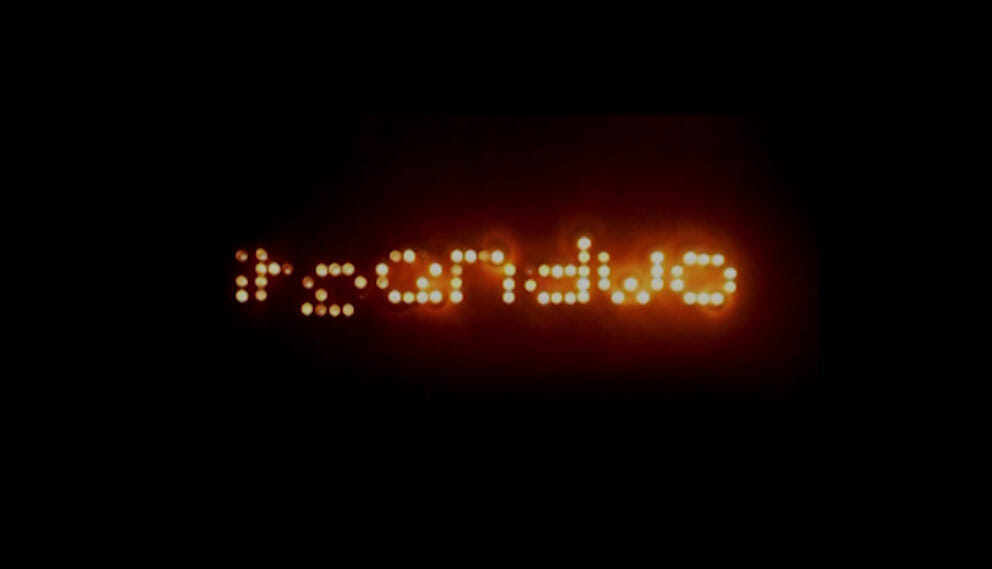
Sarah Kirsch
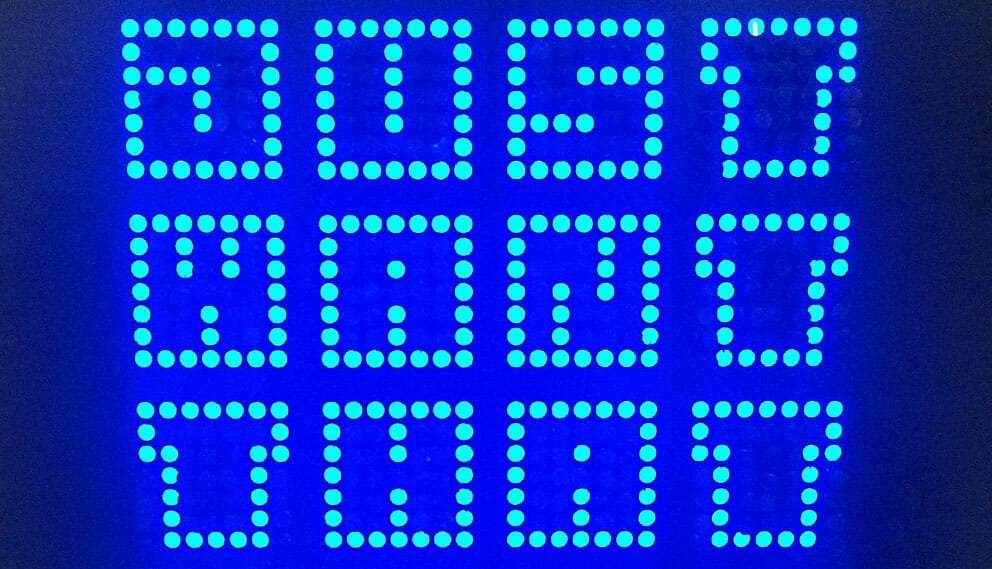
Marvin Wilhelm
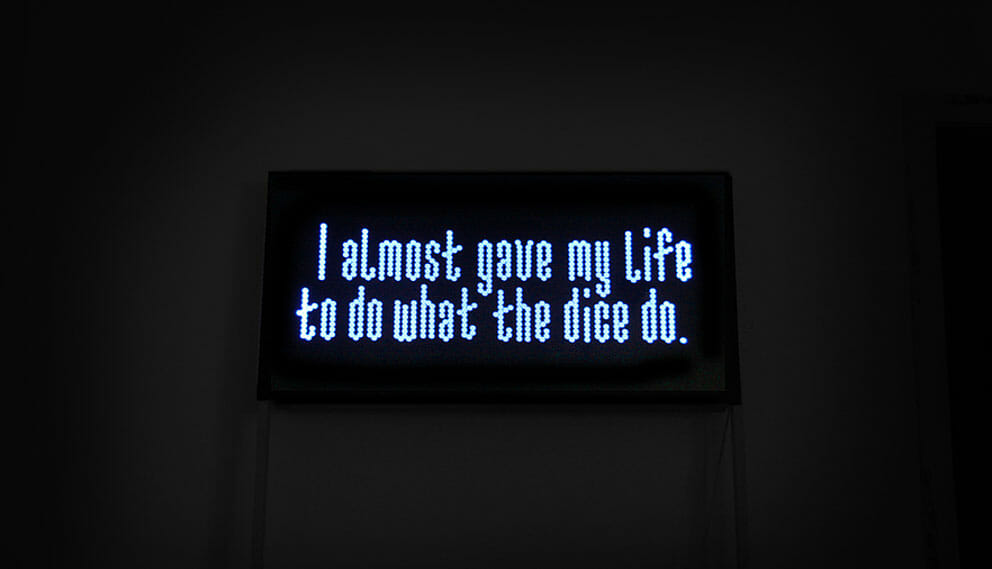
Madita Kolles
Timo Blume
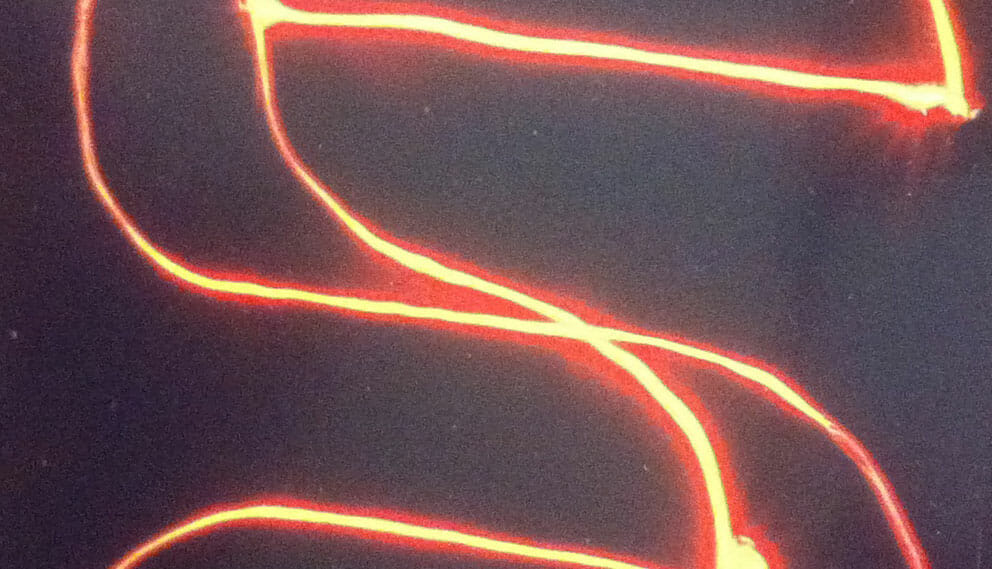
Jo Leiner
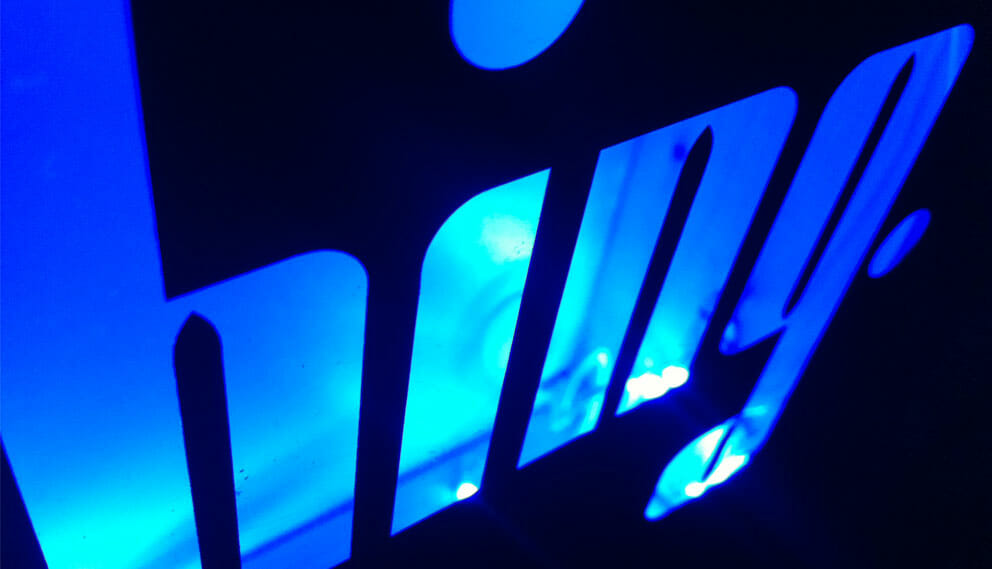
David Ebner
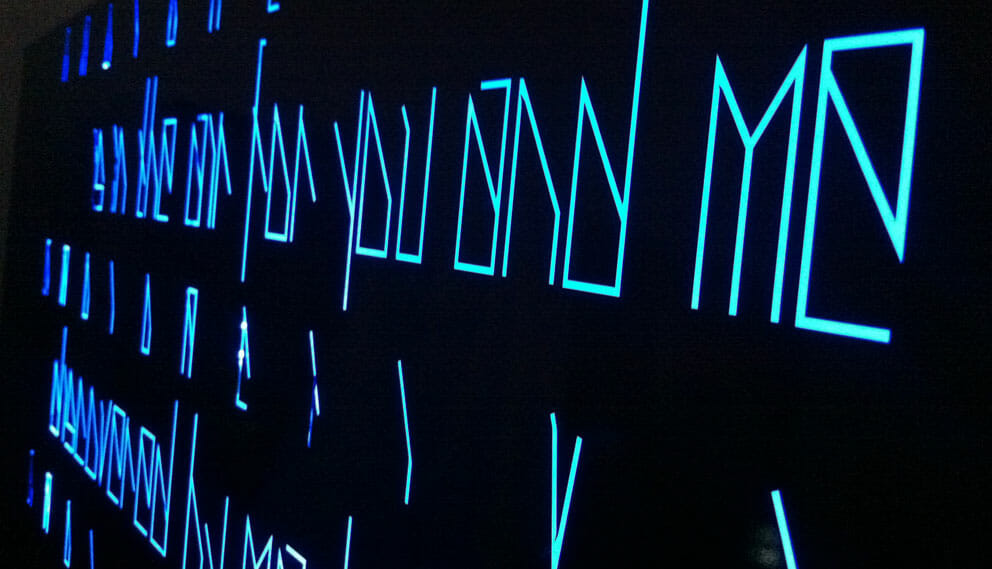
Johan Karlin
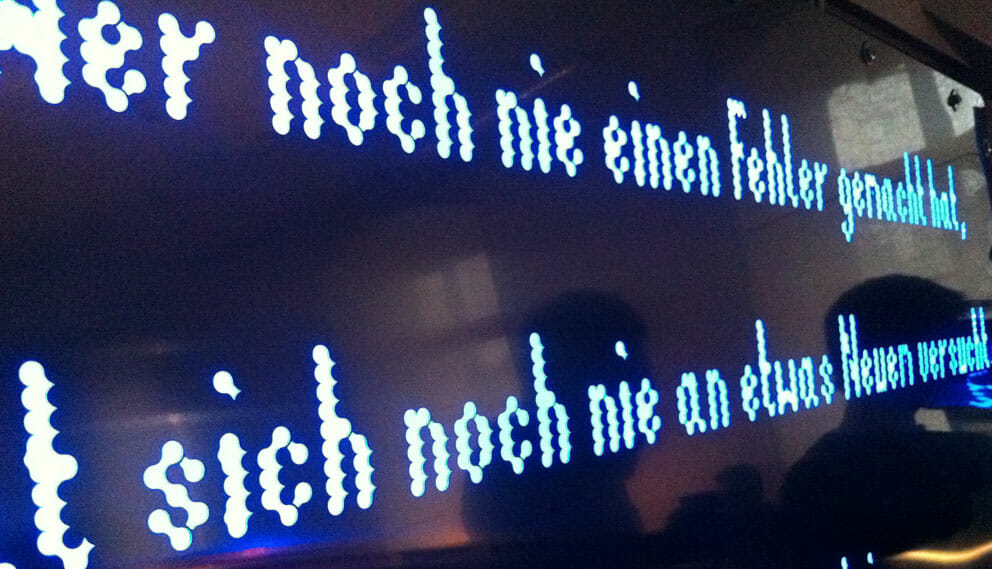
Alicia Linda Wagner